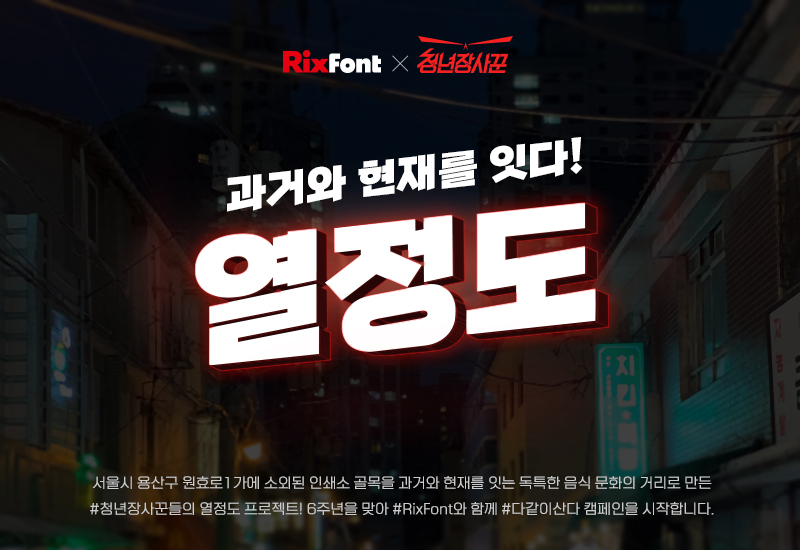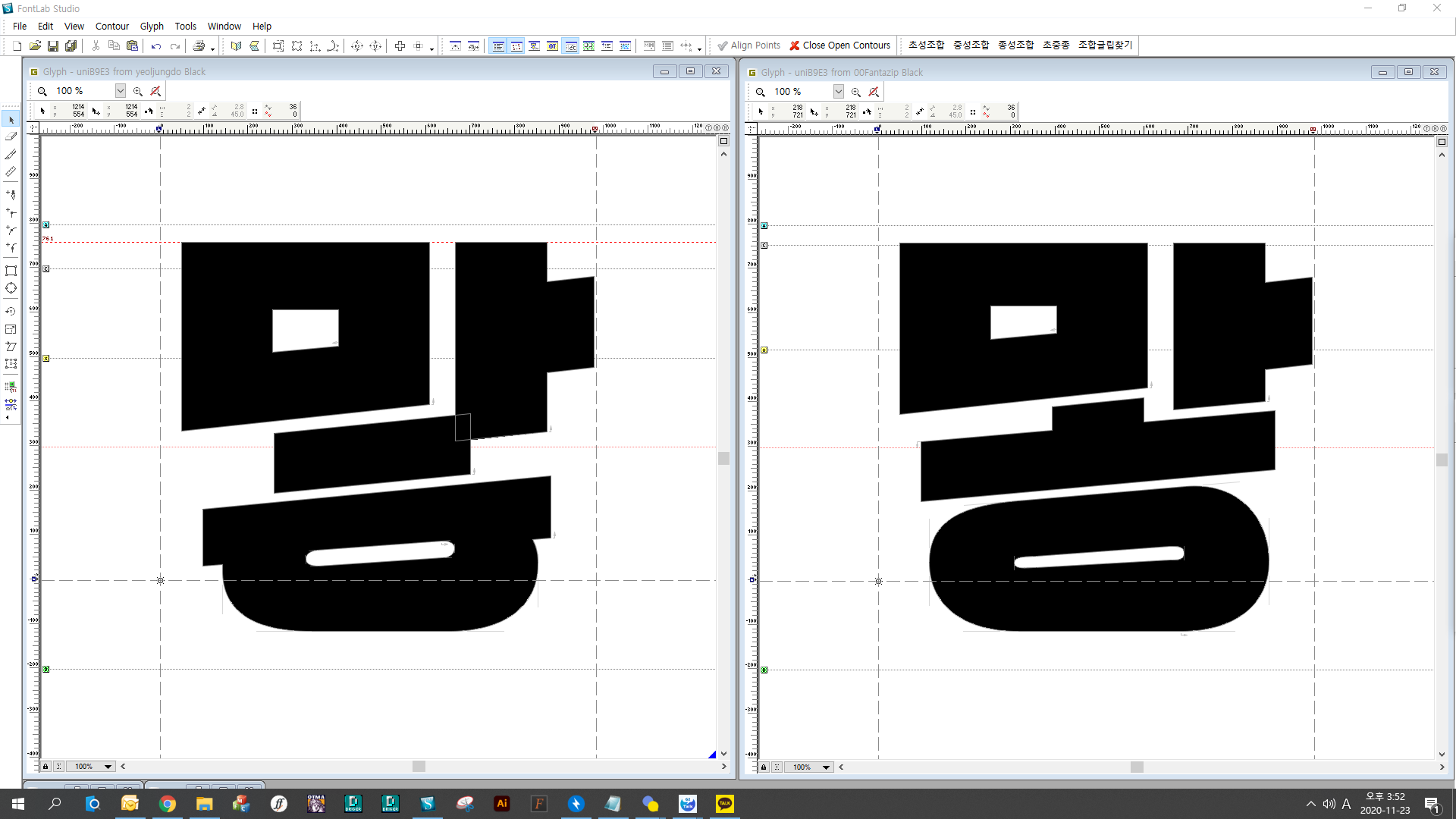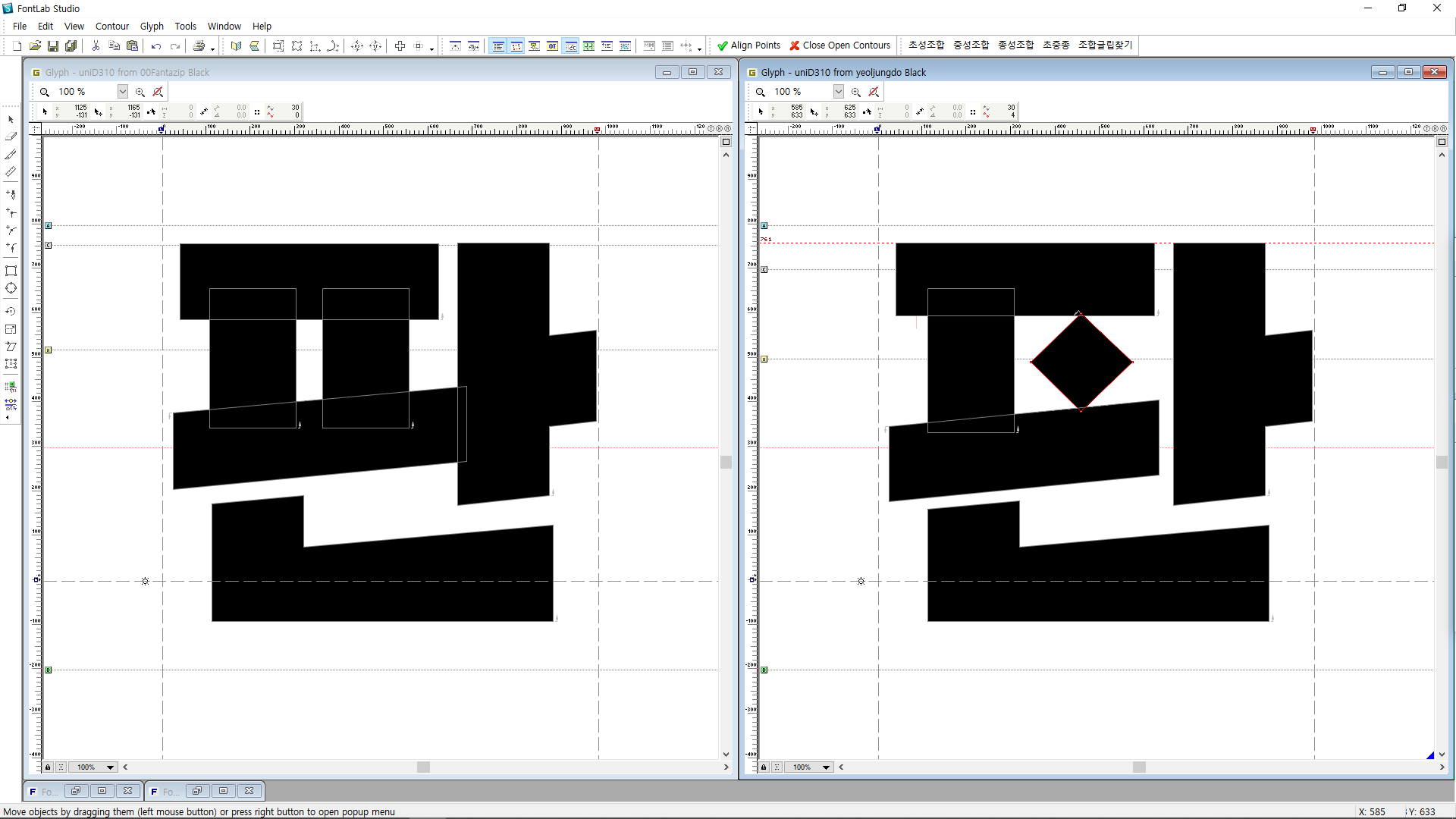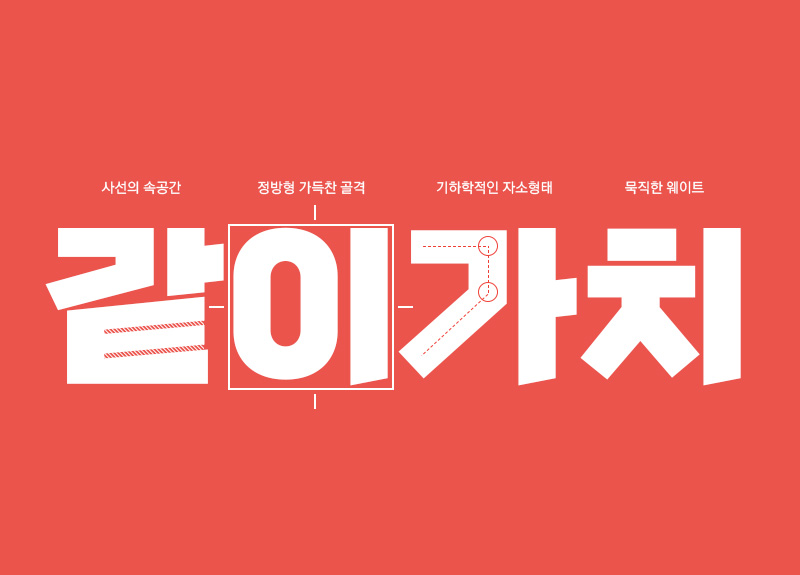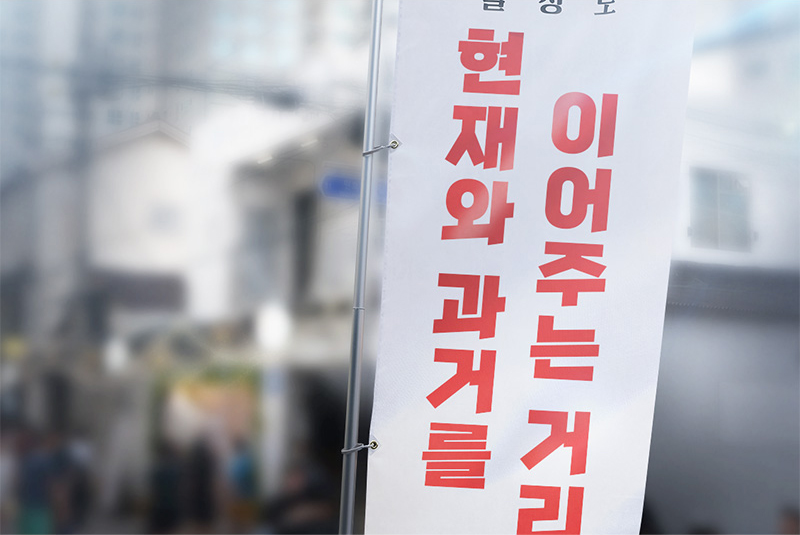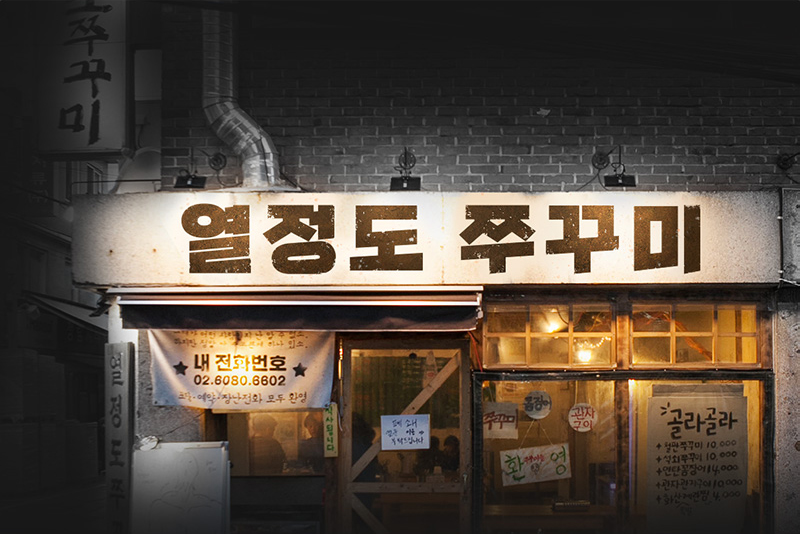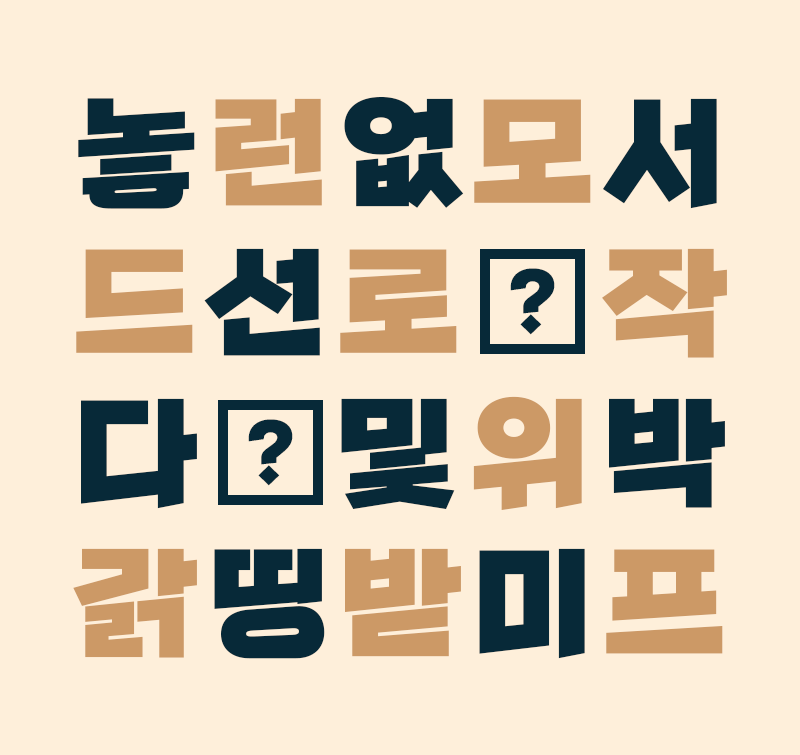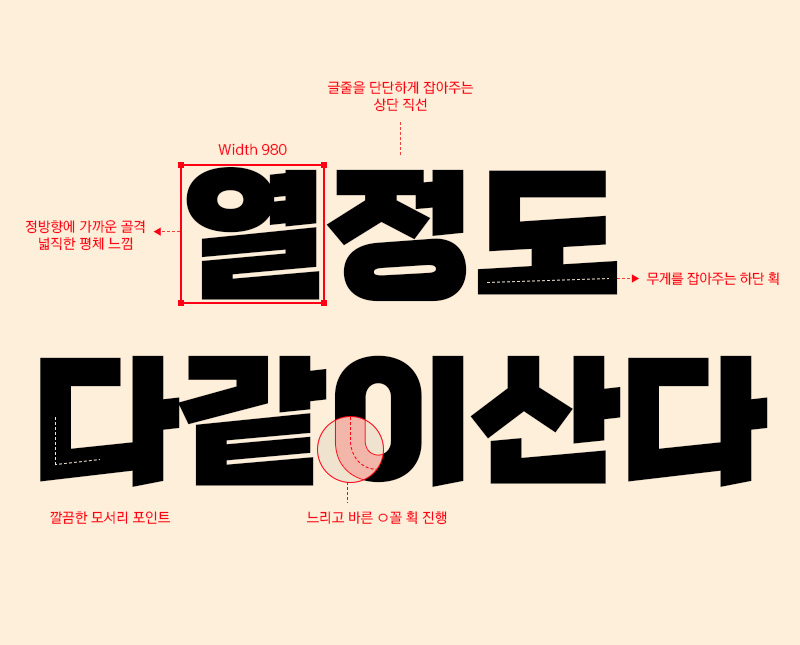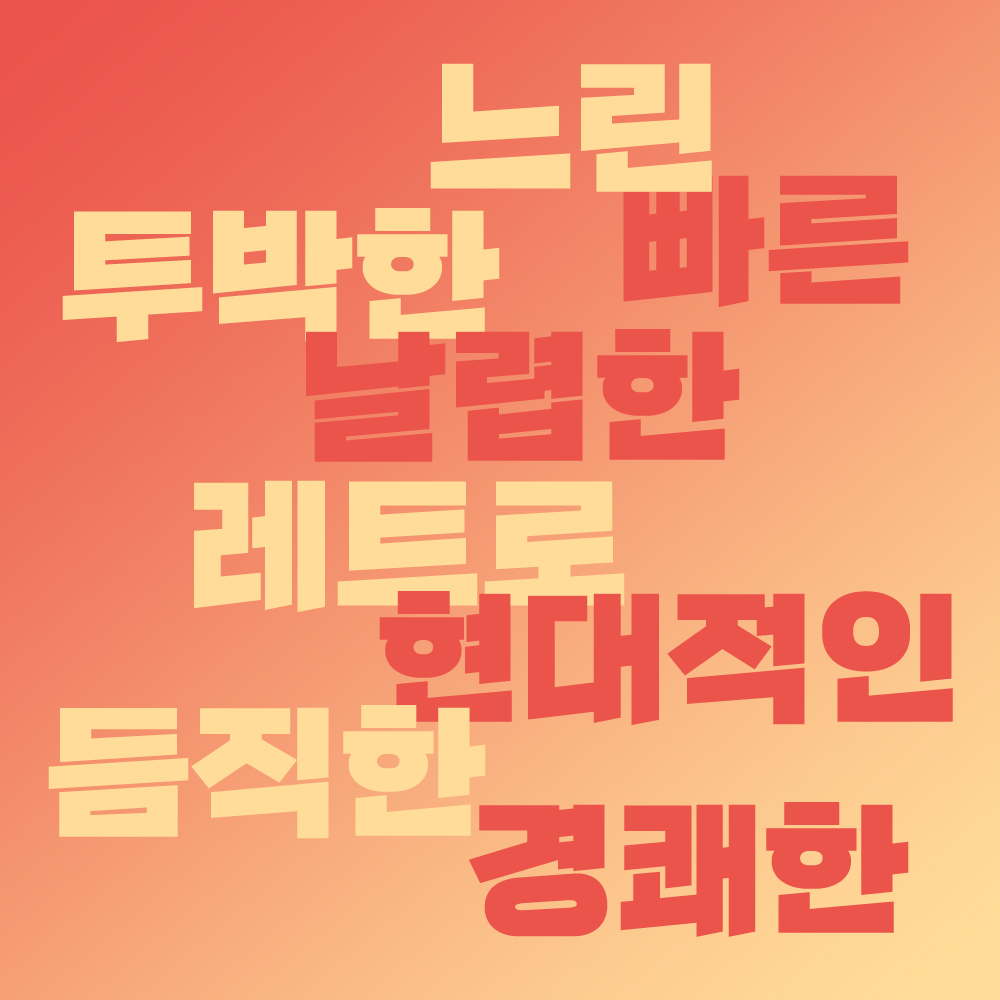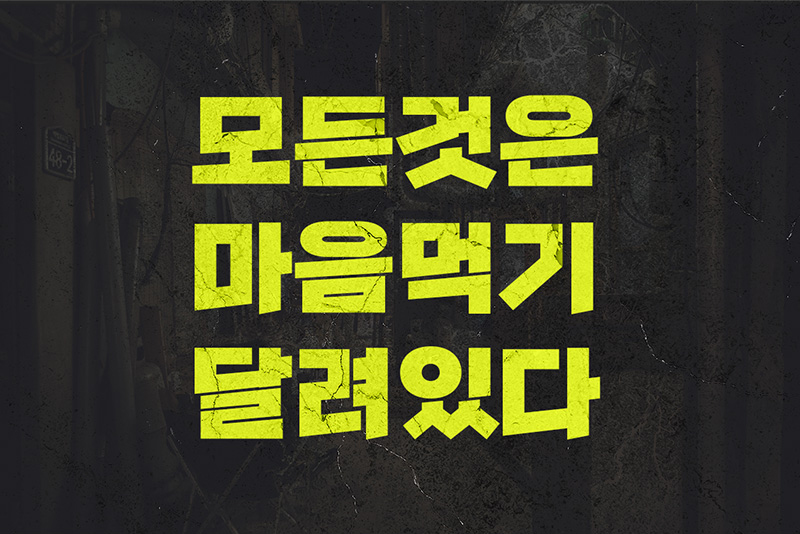
열정도 거리를 아시나요?
2014년 11월, 서울 용산구 1가의 버려진 인쇄소 공장 골목이 새롭게 태어났습니다. 고층 빌딩숲 속에 외딴섬처럼 자리 잡고 있던 소외된 거리는 '열정도'라는 이름으로 여러 음식점과 매장들이 늘어나 현재는 사람들이 찾아오는 독특한 문화, 음식의 거리로 자리잡았습니다. 「Rix열정도」서체는 이 거리를 만든 청년 소상공인 단체이자 올해 6주년을 맞은 청년장사꾼의 "다 같이 산다" 캠페인의 일환으로 함께 기획했습니다.
열정도 거리는 우리 회사가 있는 골목입니다. 이웃과도 같은 이 거리가 2020년을 앗아간 코로나19로 인해 활기를 잃은 것을 보았습니다. 많은 지역의 상권이 죽고, 힘들어 하는 사람들을 보았습니다. 어려운 시기에 함께 살아가는 우리 지역 사회가 조금은 더 나아지기를, 소상공인에게 작은 보탬이라도 되기를 바라는 마음으로 좋은 폰트를 무료로 제공하는 캠페인에 함께하게 되었습니다. 먼저 폰트를 제작한 조소희 디자이너의 이야기입니다.
폰트를 알려면 디자이너를 알아야지_폰트 디자이너 인터뷰
안녕하세요, 소희 디자이너님. 반갑습니다:) 먼저 간단하게 자기소개 부탁드려요!
안녕하세요. 한글의 규칙을 좋아하는 서체 디자이너 조소희입니다.
이번에 특별한 프로젝트에 참여하게 되셨는데, 소상공인을 위한 캠페인으로 폰트를 디자인하셨다고 들었어요. 무료로 배포되기도 하고 또 의미가 있는 폰트라 감회가 새로우실 것 같아요~!
가게에서 어떤 서체가 잘 쓰이는지 찾아보면서 즐거운 마음으로 만들었어요. 라이선스 문제는 회사에서 해결해 주셨으니 사장님들이 쉽게 사용하실 수 있게 숙고해서 디자인했습니다. 많은 분들이 사용해주신다면 더할 나위 없이 기쁘겠습니다.
폰트 자체가 힘이 굉장히 느껴지는 서체인 것 같은데요, 제작자로서 '이 폰트는 OO 한 폰트다!'라고 형용사를 붙여주신다면?
이 폰트는 반전 매력의 폰트다. 상투적이지만 가장 적절한 표현이지 않나 싶어요. 투박한 듯 섬세하고, 묵직하면서 산뜻하거든요.
Rix열정도 폰트의 디자인에 있어서 가장 신경 쓴 부분은 무엇인지?
초기에 묵직한 굵기를 설정하고 나서, 글자가 너무 무거워지지 않게 하려고 주의했어요. 쉽게 사용될 수 있도록 '편안하게', 그리고 이목을 끌 수 있게 '매력적으로' 만들자 생각하면서요. 이를테면 받침 ㅎ의 형태가 초기 스케치에서는 선 꼭지였는데, 시각적으로 걸림 없이 빠르게 지나가는 게 더 좋을 것 같아 누운 꼭지로 변형했습니다.
매력적인 요소를 넣을 때도, 안정성과 가시성 가운데서 균형을 잡으며 과하지 않게 디자인했어요. 현재 마침표 디자인인 마름모 형태도 스케치 단계에서는 ㅍ의 빗침 획과 ㅌ의 덧줄기에 들어가 있었는데, 욕심을 자제하고 생략했죠. 결과적으로 더 편안하면서도 매력적인 서체가 된 것 같아 만족스럽습니다.
마지막으로 폰트 디자이너로서 목표가 있다면?
고착화되지 않는 디자이너가 되려고 해요. 서체를 만들 때 제 특징이 녹아 나올 수밖에 없겠지만, 매번 다른 스타일로 만들어보려고 노력합니다. 항상 연구하고 고민해서 늘 새로운 것을 알아가고 배워가고 만들어내고 싶어요.
같이의 가치, 소상공인을 위한 서체
Rix열정도는 코로나19로 어려움을 겪고 있는 소상공인들을 위해 저작권 걱정 없이 어디에나 사용 가능한 폰트로 제작했습니다. 기존의 소상공인들은 매장의 로고, 간판, 배너 등 디자인에 사용한 폰트들로 인해 저작권 소송에 걸리거나 영업에 피해를 본 경우가 종종 있었습니다. 그런 걱정 없이 편하고 자유롭게 쓸 수 있는 폰트입니다.
과거와 현재를 이어주다.
열정도는 옛 기와, 붓으로 쓴 상호, 복고풍의 가게들과 높이 솟은 고층 건물들, 세련된 인테리어의 현대적인 매장들이 함께 상생하는 거리입니다. 이런 상반된 이미지가 조화롭게 섞여 있는 것이 Rix열정도 서체의 특징이기도 합니다.
묵직하면서도 속도감이 느껴지는 형태. 정방형에 가까운 꽉 찬 모듈이 복고적인 느낌을 주지만, 깔끔하고 시원시원한 사선의 획이 세련된 느낌도 주는 서체입니다.
열정도체는 느리고, 투박하고, 복고적이고, 듬직한 동시에 빠르고, 날렵하고, 현대적이며 경쾌합니다.
상반된 두 특징이 조화롭게 섞인 독특한 매력의 서체입니다. 이미지 샘플들을 보면서 그 매력을 더 알아볼까요?
| Rix열정도 적용 이미지 샘플
열정 넘치는 문구들! 힘 있는 서체의 특징이 문구를 더욱 돋보이게 해 줍니다.
매장에서 메뉴를 보여주는 용도로 많이 쓰는 액자나 배너 형태의 사인물을 제작할 때에도 가시성이 중요하겠죠? 포스터나 메뉴판 등의 인쇄물에도 눈에 확 띄는 글씨로 홍보 효과를 높일 수 있습니다.
문구를 넣은 디자인 굿즈에도 쓰일 수 있는데요, 홍보를 위한 티셔츠 제작이나 핸드폰 케이스, 다양한 상품에 무난하면서도 세련된 디자인으로 활용할 수 있습니다. 로고로 사용하여 여러 상품들을 제작 판매할 수도 있으니 활용도가 높을 것 같아요.